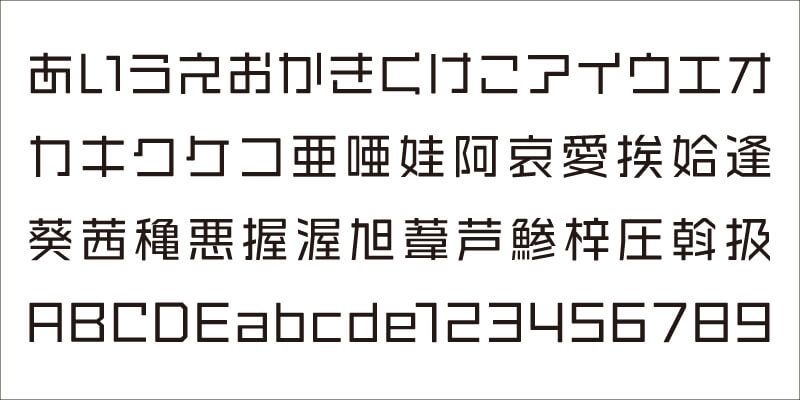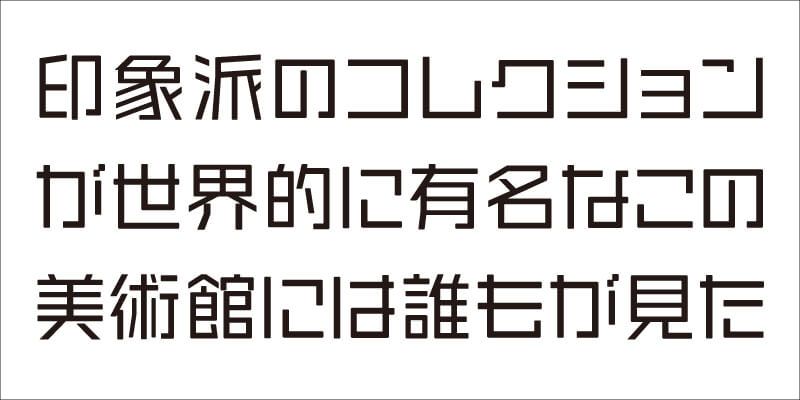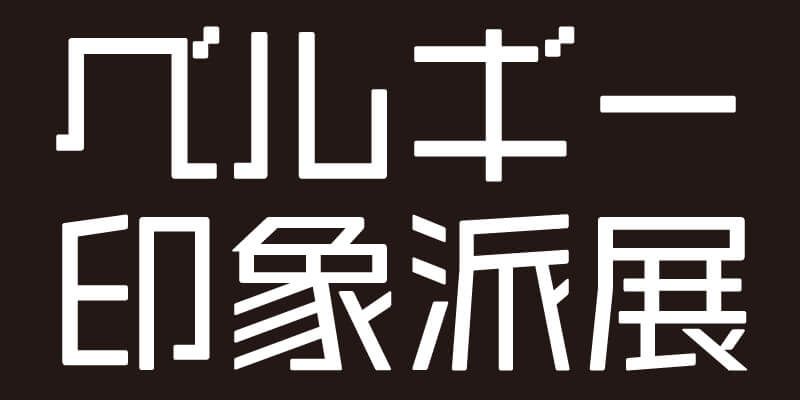
Basierend auf der VDL-LineG, deren Zeichen nur aus geraden Linien bestehen, ist die VDL-LineGR eine gotische (serifenlose) Schrift, die sich durch Striche mit abgerundeten Ecken auszeichnet. Wie die VDL-LineG hat dieses Design eine visuelle Schärfe und Stärke, aber auch einen Sinn für Ruhe.